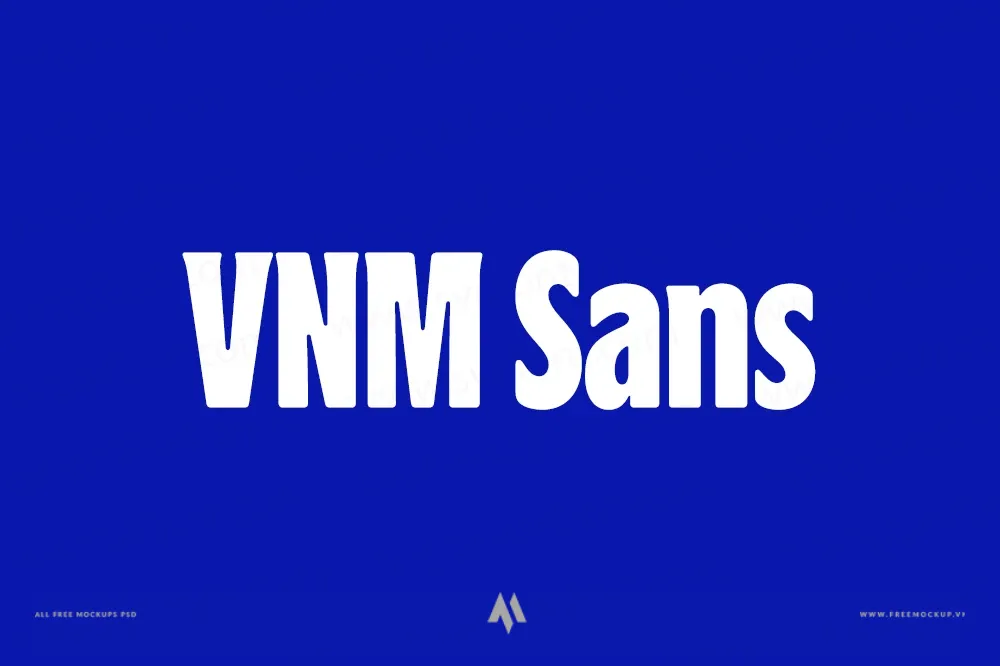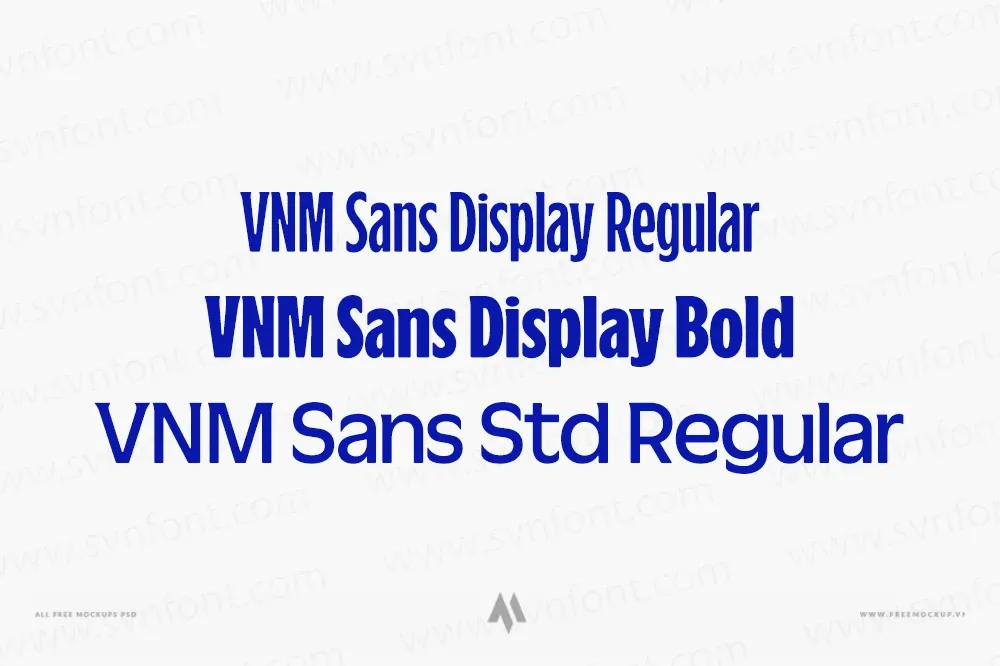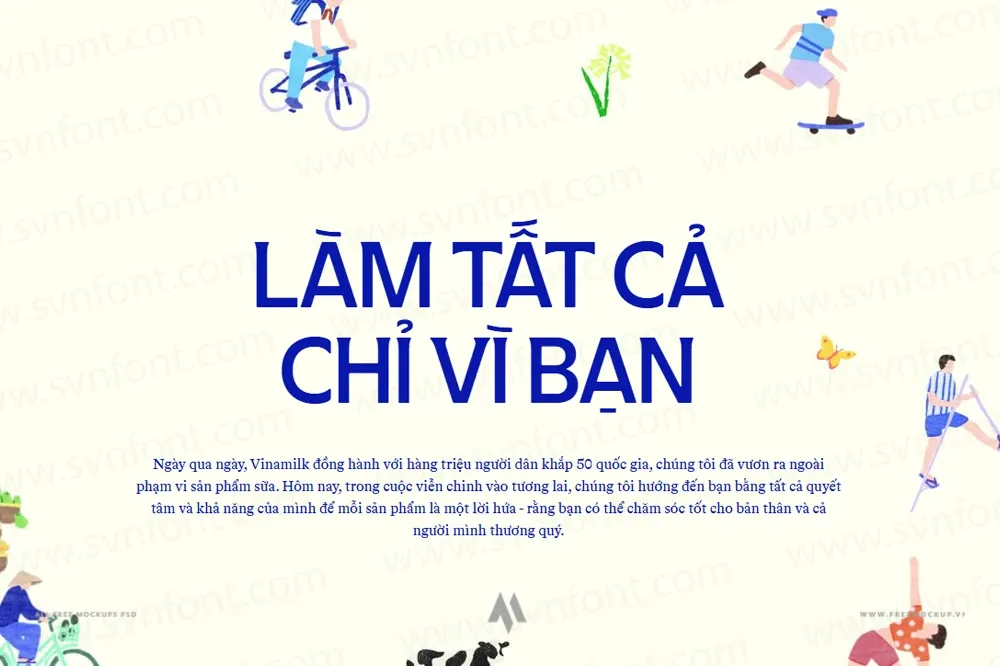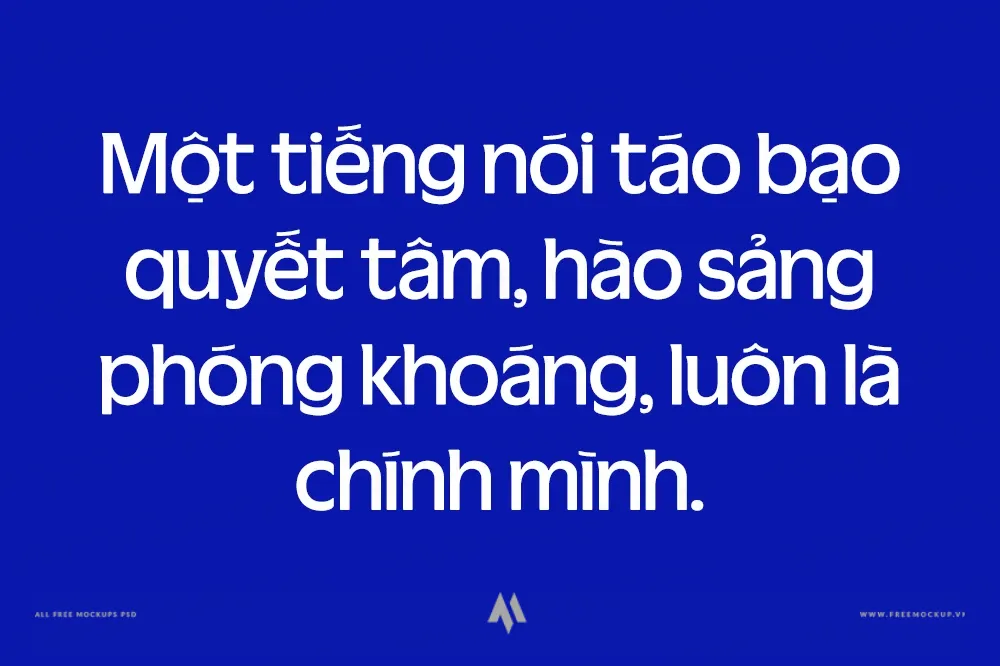
Bộ Font VNM Sans (Nhận diện thương hiệu Vinamilk) là hệ thống phông chữ độc quyền được thiết kế riêng trong chiến dịch tái định vị thương hiệu lịch sử của Công ty Cổ phần Sữa Việt Nam (Vinamilk). Mang tinh thần hiện đại, tối giản và phóng khoáng, VNM Sans đại diện cho bước chuyển mình mạnh mẽ, truyền tải nguồn năng lượng trẻ trung, tươi mới và kết nối sâu sắc với thế hệ người tiêu dùng tương lai.
Ngôn ngữ thiết kế Custom Typography: Được “đo ni đóng giày” độc quyền cho Vinamilk với các biến thể linh hoạt (từ Sans cơ bản, Display đến các nét vẽ tay ngẫu hứng), tạo nên dấu ấn thị giác độc bản và không thể nhầm lẫn.
Phong cách Geometric Sans hiện đại: Đường nét chữ đậm đà, cấu trúc hình học chuẩn mực, khoảng cách ký tự thoáng đãng giúp tối ưu hóa khả năng hiển thị trên cả bao bì in ấn lẫn màn hình số.
Tinh thần trẻ trung & Tự tin: Phá vỡ khuôn mẫu truyền thống cũ kỹ để thể hiện tinh thần bứt phá, năng động, mang đến nguồn cảm hứng thị giác tươi mới và đầy bản lĩnh.